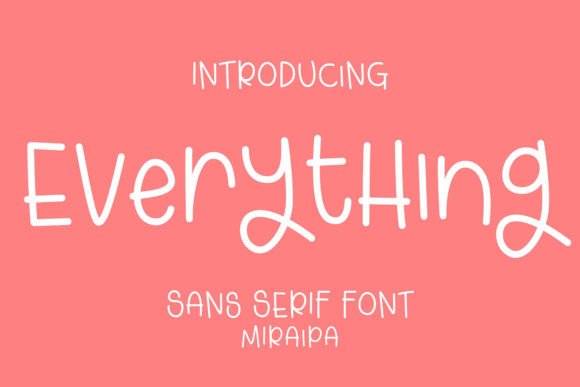
Everything
適切なデザイン要素を見つけるのは難しい場合がありますが、Everythingは作品を即座に引き立てる優れたコレクションを提供します。
POD(オンデマンド印刷)製品、結婚式の招待状、またはソーシャルメディアのグラフィックを作成している場合でも、Everythingは理想的です。